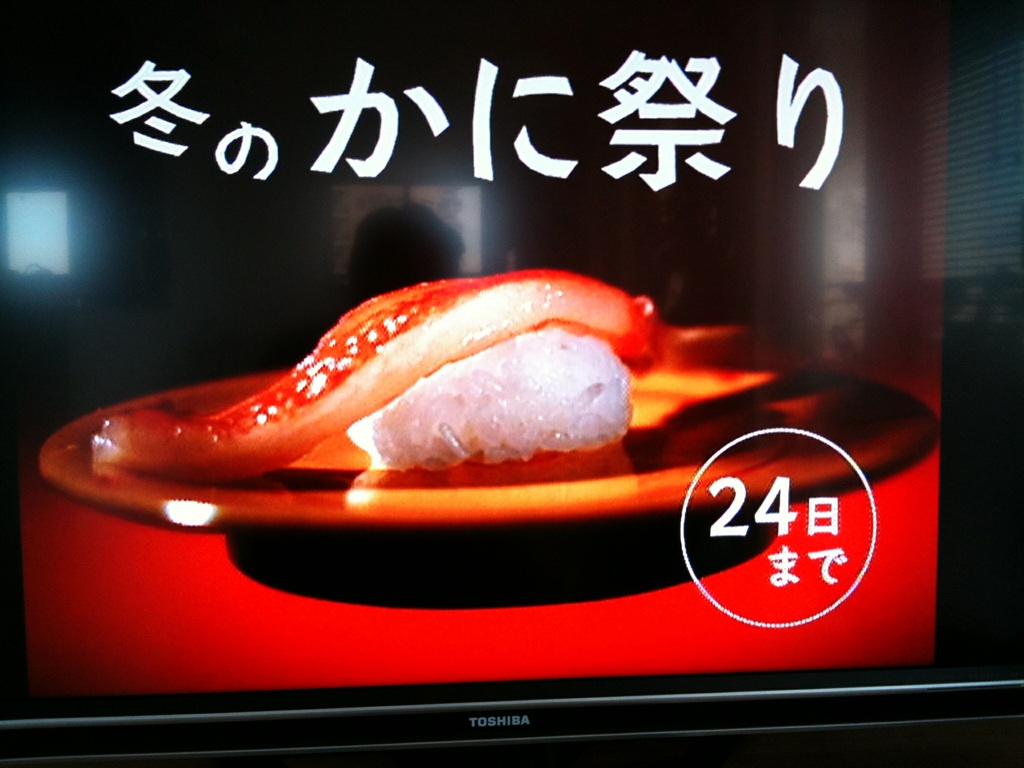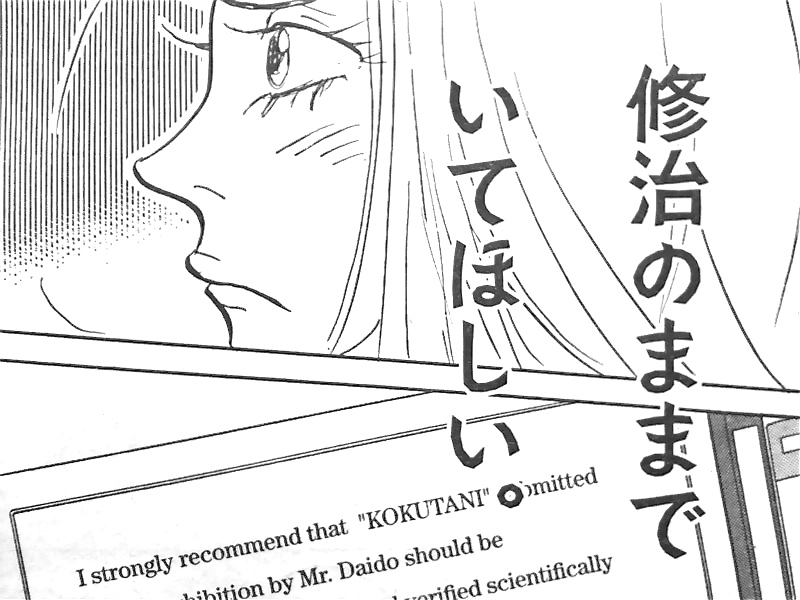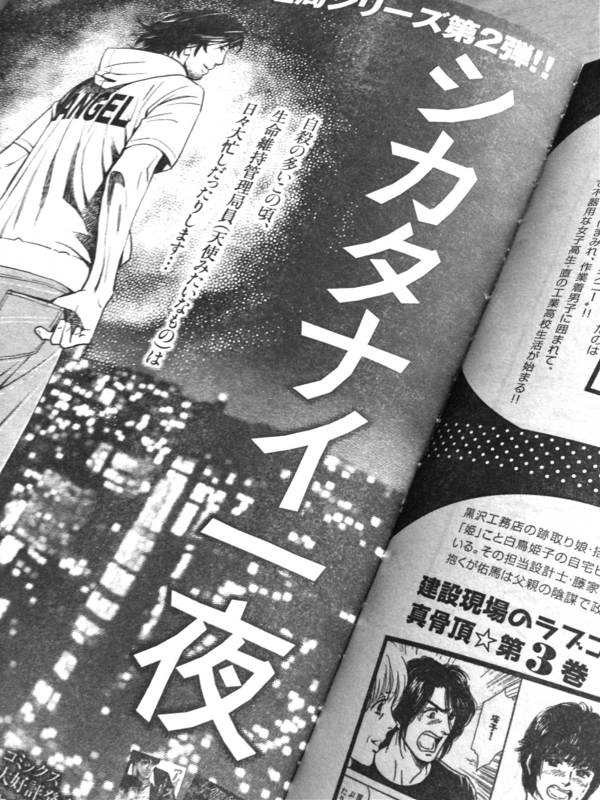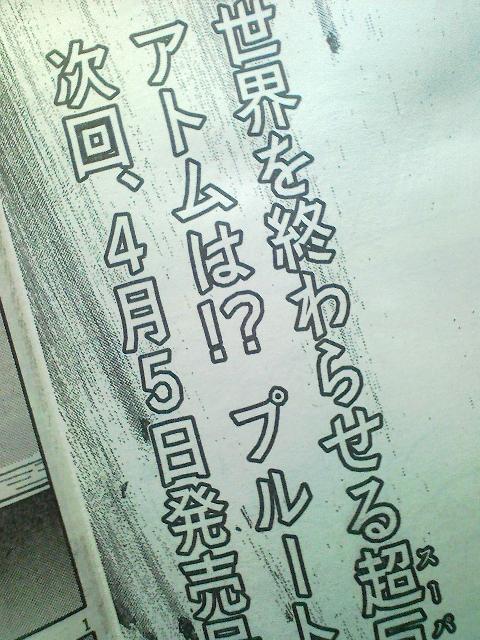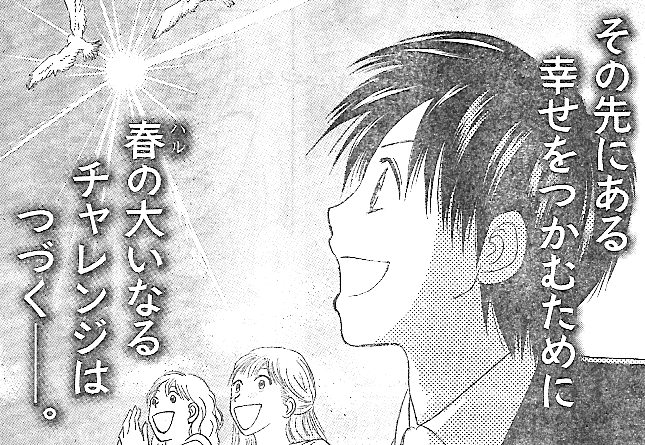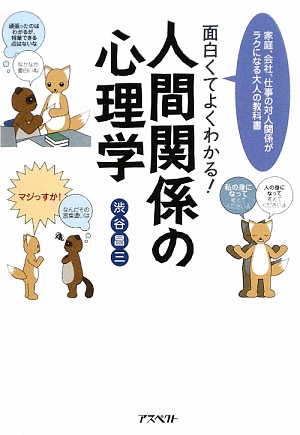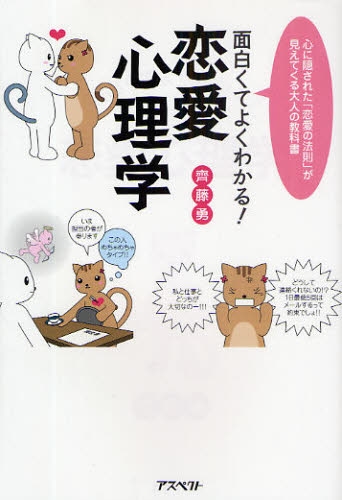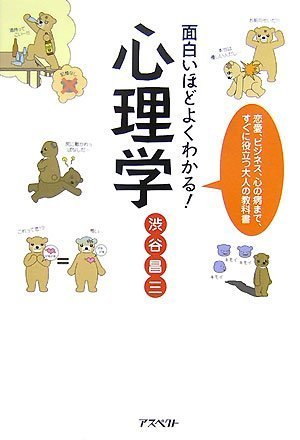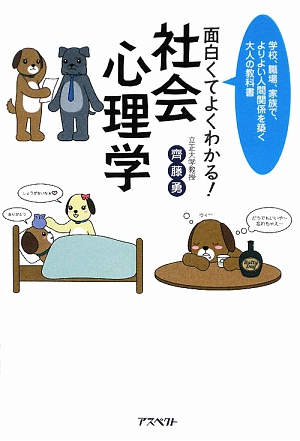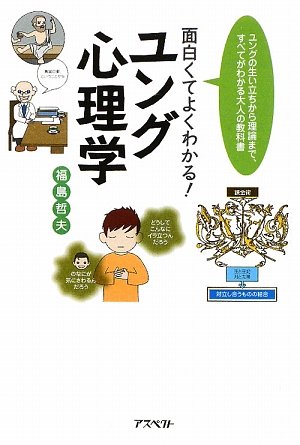
書名:願いがかなうふしぎな日記
著者:本田有明
発行:PHP研究所
FC2ブログの管理ページに貼られていたバナー広告での『あられ』使用例です(左上の青い文字)。
時々、墨東とあられがなぜか似たようなフォントに見えてしまうのです…。
墨東とあられを混同する人も、たまにいらっしゃいますよ…。
かな文字のティストが似てるんでしょうね。
ラジオ番組「音楽遊覧飛行」というサイトの
タイトルページから。
タイトル文字と出演者の名前にも使われて
います。
NHKのFM放送ですね。
漫画雑誌の扉ページ  さとうゆたか  2012年4月11日(水) 15:34
スピリッツに連載中の「明日のない空」という漫画。
本の書名  さとうゆたか  2012年3月11日(日) 9:18
書名:ふるさとをあきらめない
著者:和合亮一
発行:新潮社
こちらは雑誌に掲載されている広告。
本の題名  さとうゆたか  2012年1月28日(土) 16:48
書名:金の成る木
著者:シドニィ・シェルダン 超訳/天馬龍行
発行:アカデミー出版
こちらは、この本の新聞広告。
書籍の表紙  さとうゆたか  2011年12月9日(金) 8:05
左下の出版社名以外は、全て「あられ」書体です。
書名:ひとさじで料亭の味!魔法の糀レシピ
著者;浅利妙峰
発行:講談社
パン屋さん  さとうゆたか  2011年10月2日(日) 21:35
北千住本町センター商店街にある店「ぷちブレッド百乃苺」。